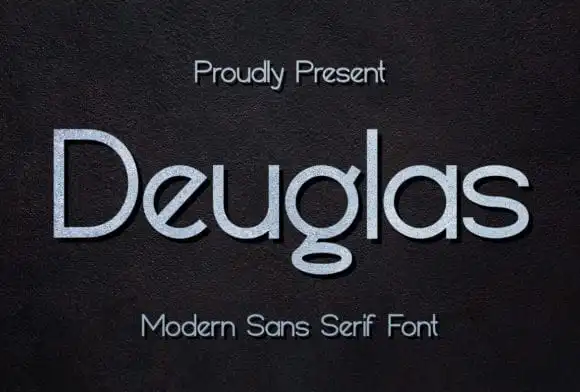
Deuglas Sans Serif Font – Download Grátis
Introduzimos a Deuglas Sans Serif Font, uma escolha perfeita para quem busca clareza em seus projetos digitais sem abrir mão do charme minimalista e neat. Suas linhas leves e sua aparência moderna criam um contraste harmonioso com fontes serifadas mais elaboradas, tornando-a uma opção ideal para subtítulos decorativos. Esta elegante fonte de sans serif é designada pelo sartstudio e pode ser facilmente adaptada a diversos tipos de projetos. Seu estilo minimalista e limpo permite que se integre em qualquer tipo de projeto gráfico sem perder seu poder visual, tornando-a uma opção perfeita para aqueles buscando destaque em seus trabalhos. Experimente adicionar Deuglas Sans Serif Font às suas próximas criações e veja como ela pode transformar a aparência de seu design.